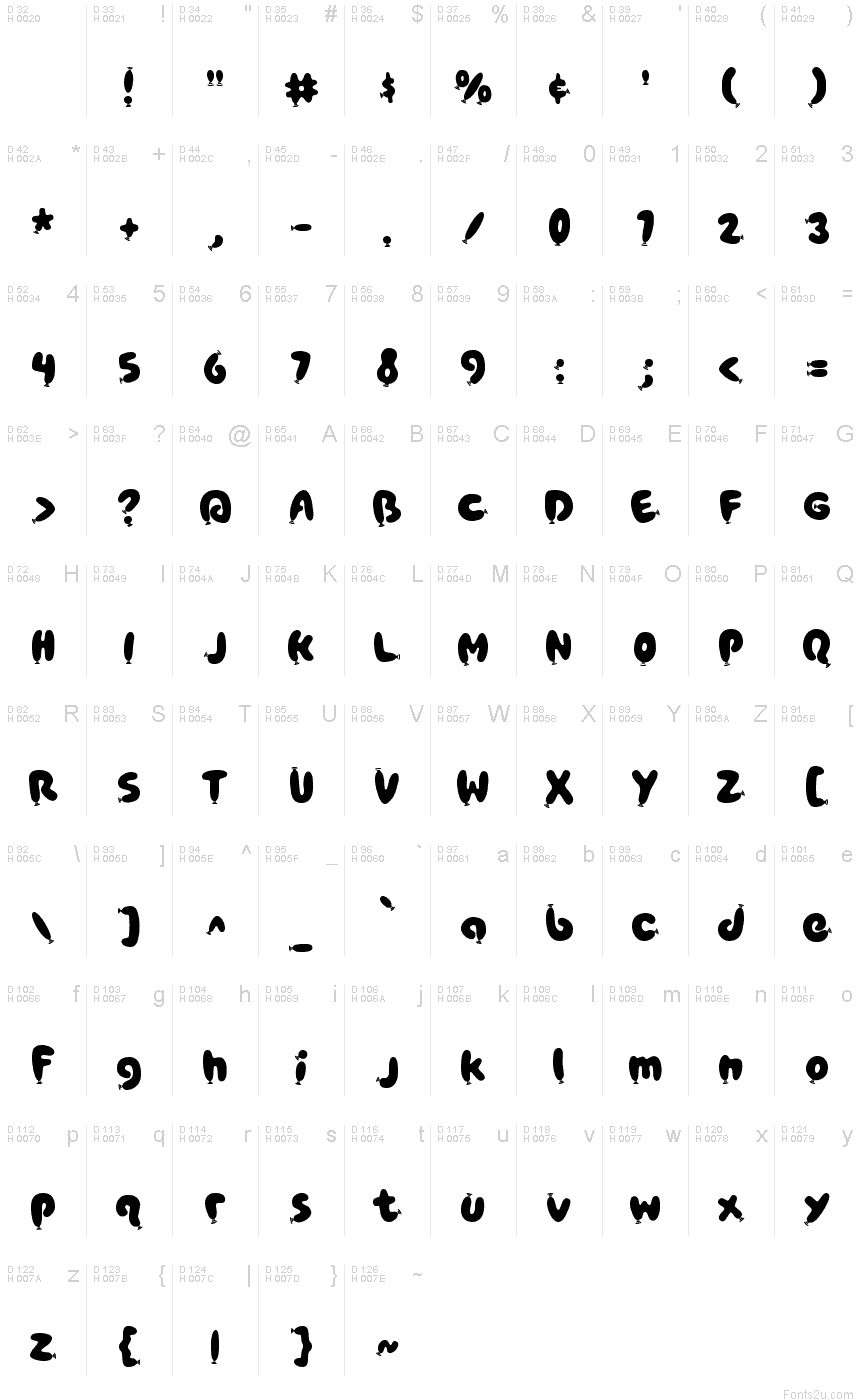
Poppy AOE, di Astigmatic One Eye Foundry, è un font display gratuito in stile cartoon, caratterizzato da un andamento vivace e simile a quello dei palloncini. Le lettere appaiono gonfie e leggermente ricadenti, con forme rotonde e corpose e piccole estremità annodate che fanno sembrare l'intero alfabeto come un mazzo di palloncini a elio che ondeggiano insieme.
Questo rende questo font gratuito una scelta naturale per volantini di feste, copertine di libri per bambini, packaging di caramelle, loghi giocosi e brevi titoli di poster dove la sagoma gonfiata fa la sua bella figura. Si adatta anche a titoletti e scritte d'impatto, poiché quelle forme morbide e piene portano con sé un'atmosfera allegra e fluttuante, anche in linee molto brevi.